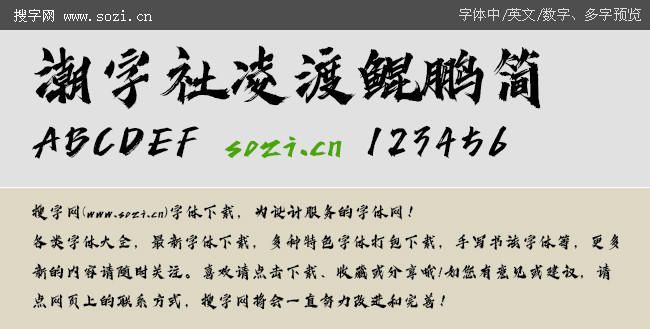
潮字社凌渡鯤鵬簡
搜字網(wǎng)提供一款潮字社凌渡鯤鵬簡中文手寫字體下載,該字體筆力勁健挺拔,瘦勁精勻,流露出“險勁瘦硬、崛起削成”的歐陽詢書意,其整體效果出色,適用于書籍封面、廣告包裝、海報設(shè)計等領(lǐng)域!驹撟煮w為個人非商用版,如需商用請聯(lián)系銳字工房購買授權(quán)】